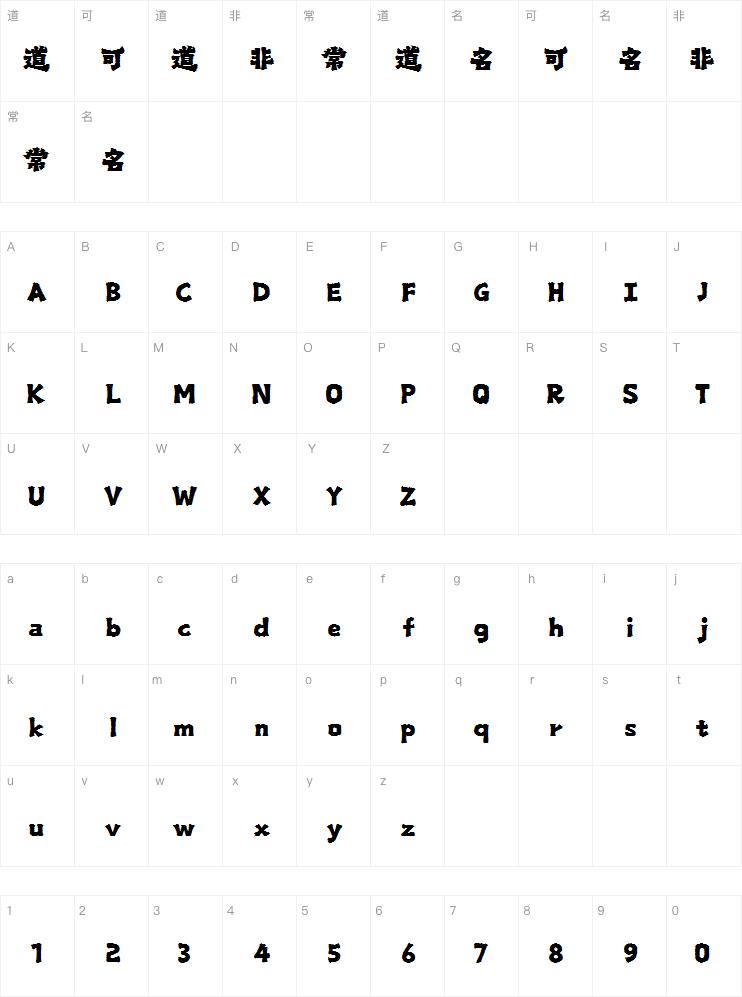
山海爨体手书,是一款全新的字体,包含汉字9169个,符号200+个。该字体灵感来源于晋魏时期的金石爨体碑刻,是一款具有碑刻味道的书写字体。字体运用独特的毛笔笔锋,狂野有力,非常醒目!在制作过程中融入魏碑的手写方式,同时又兼具隶书的书写风格,注重材料的性能发挥,狼毫侧锋饱满用墨、中锋枯笔形成游丝飞白,从而使得该字体字形古朴浑厚,在浑厚的同时而又极富张力。它的笔画充满力量感的同时,又蕴含着朴拙感。在粗细的纵横间,拥有非常规的张力特性。笔画的飞白效果使字体的气息更加流畅,笔画间的关系密不可分,同时也增加了字体的自由洒脱之感。这款字体古韵悠扬而不失灵动,静中有动,收放有序,适合作为标题字体应用于书籍封面、影视标题、展览广告等多种场景。